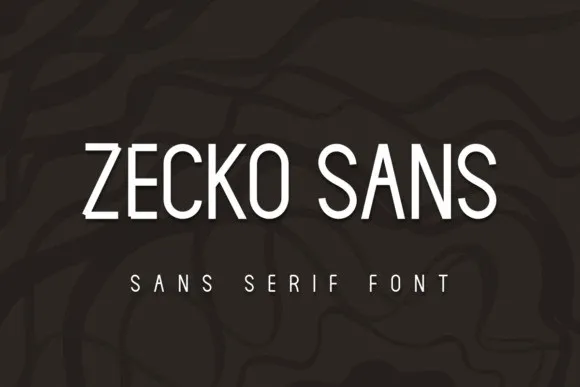
A Zecko Sans Serif Font é uma escolha perfeita para designers que buscam simplificação e elegância num tipo sans serif moderno. Sua simplicidade e forma pura permitem que você use a fonte para criar logomarcas, identidades de marca, materiais de casamento, convites, assinaturas, selos e mais. Devido à sua natureza casual, é perfeita para uma ampla gama de projetos de design, desde o branding até as seções de cabeçalhos e designs para festas. Fabricada pelo font designer deedeetype, a Zecko Sans Serif oferece um estilo elegante que vai do básico ao sofisticado em qualquer projeto. Com ela na sua arsenal de ferramentas de design, você pode criar uma variedade incrível de trabalhos visuais, tornando seu trabalho ainda mais profissional e único.